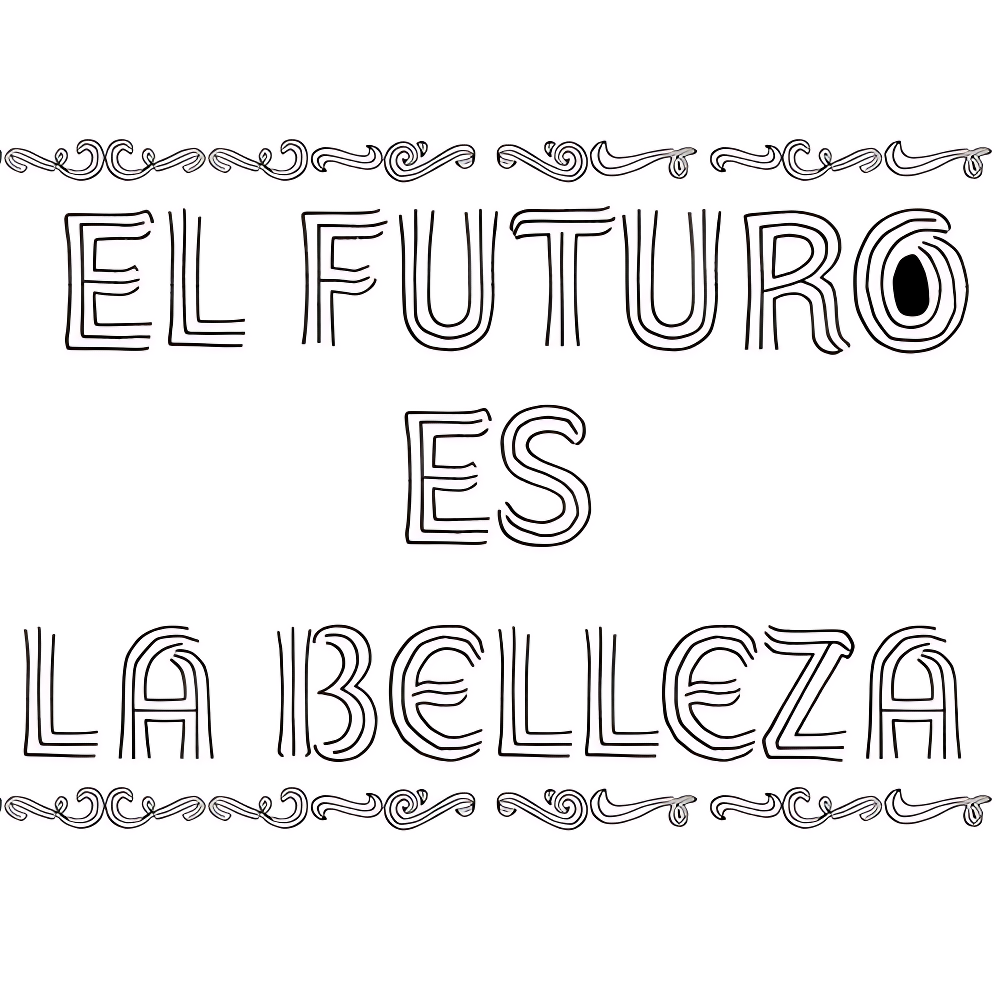
Elah Spring
| Descripción | Se trata de una versión más artística de "Elah Pro" que contiene la versión normal y la alternativa, así como Dingbats y ornamentos. Elah Spring contiene 4 estilos |
| Clasificación | Títulos, Experimental |